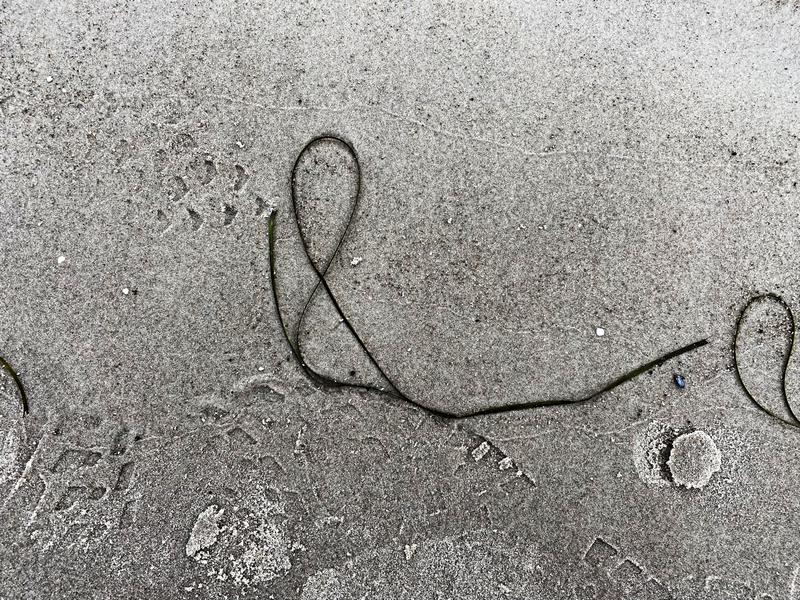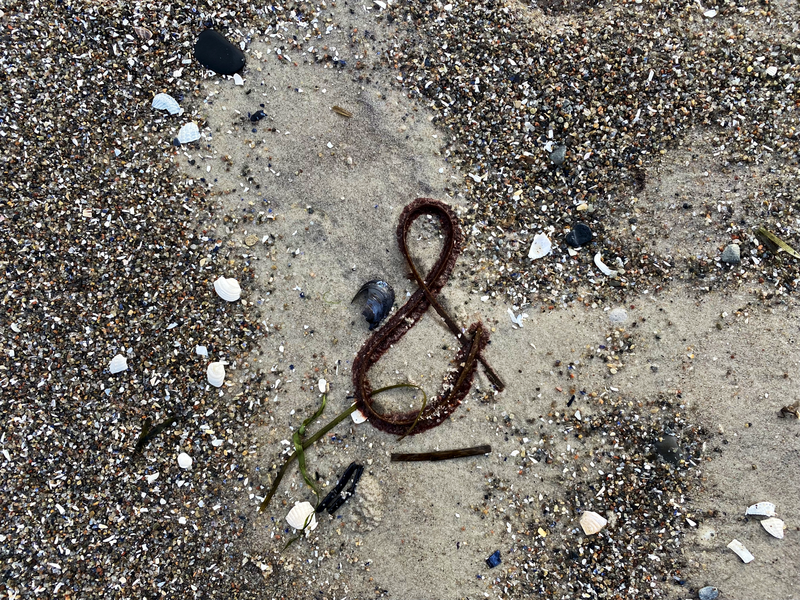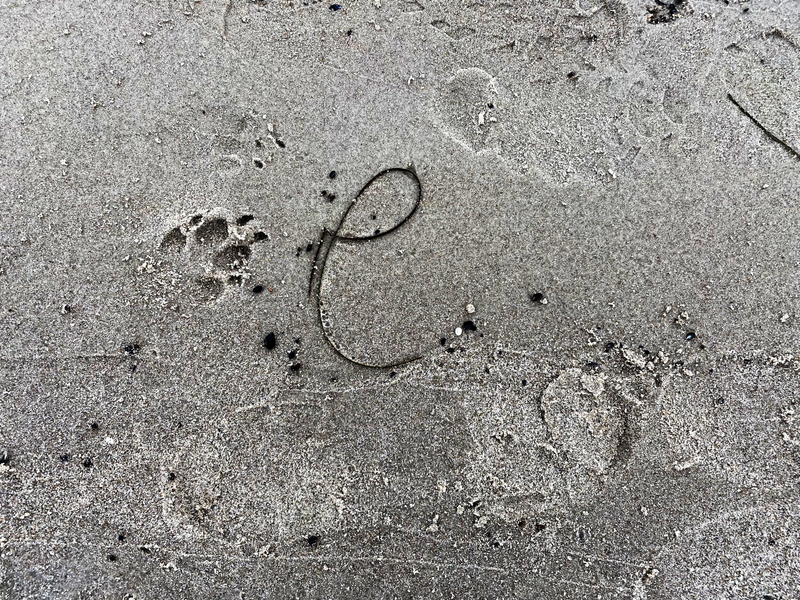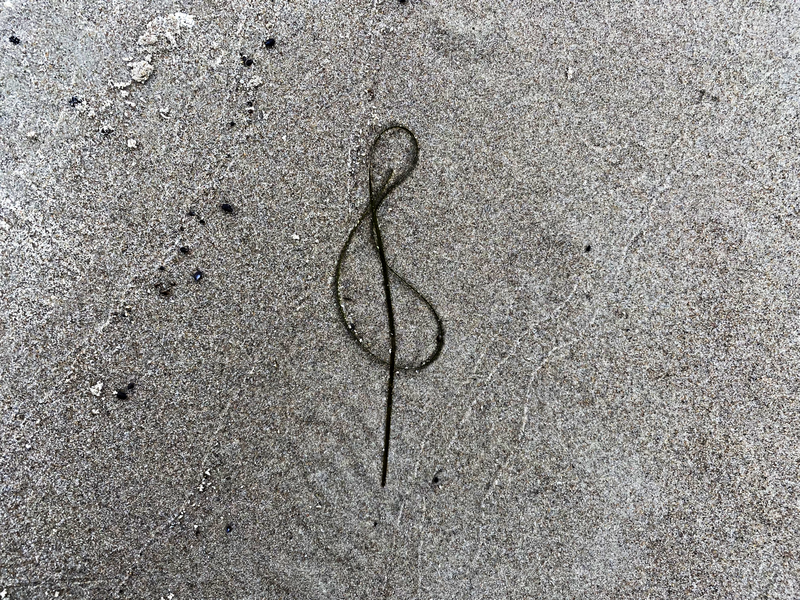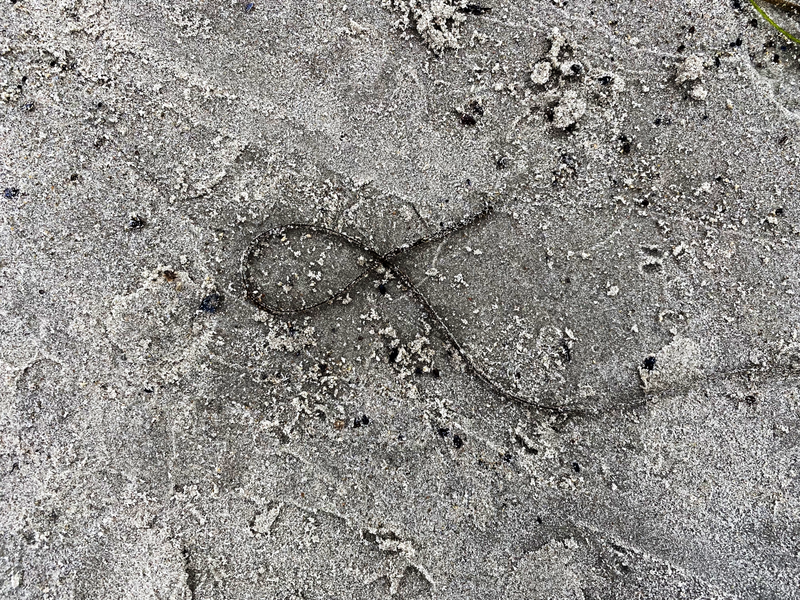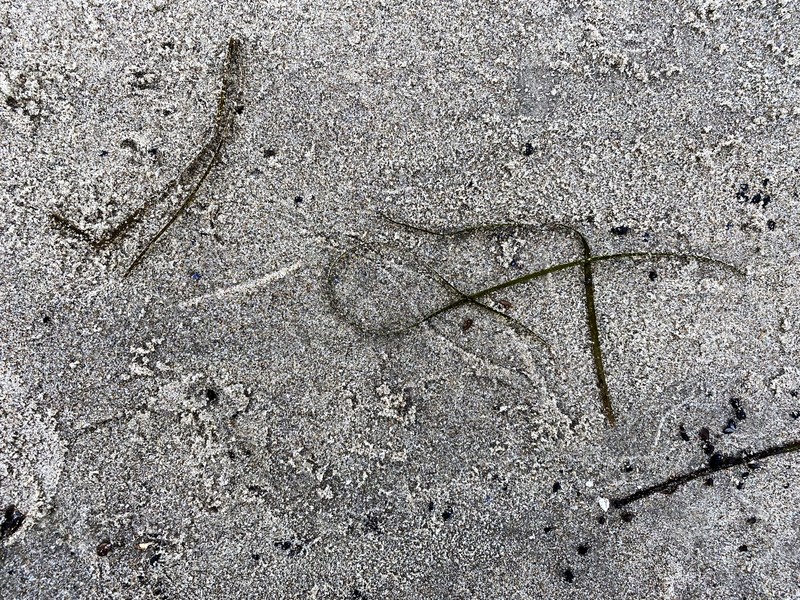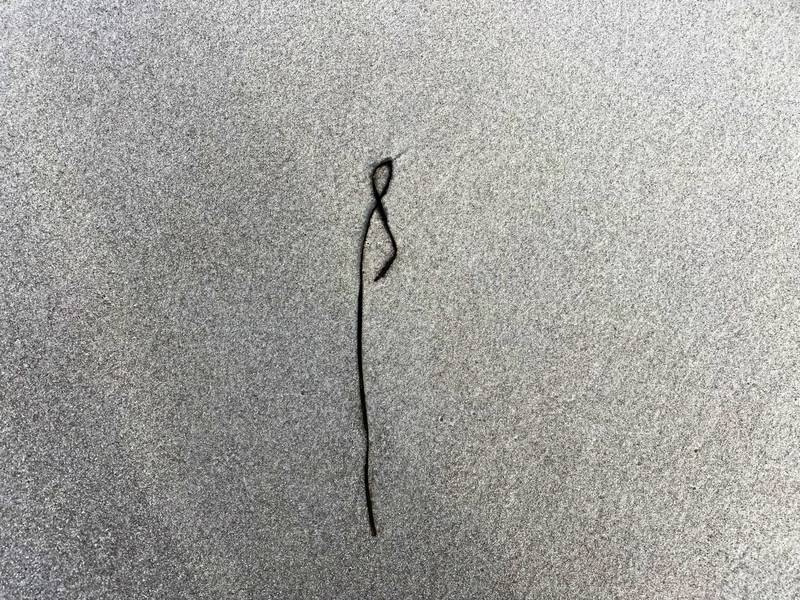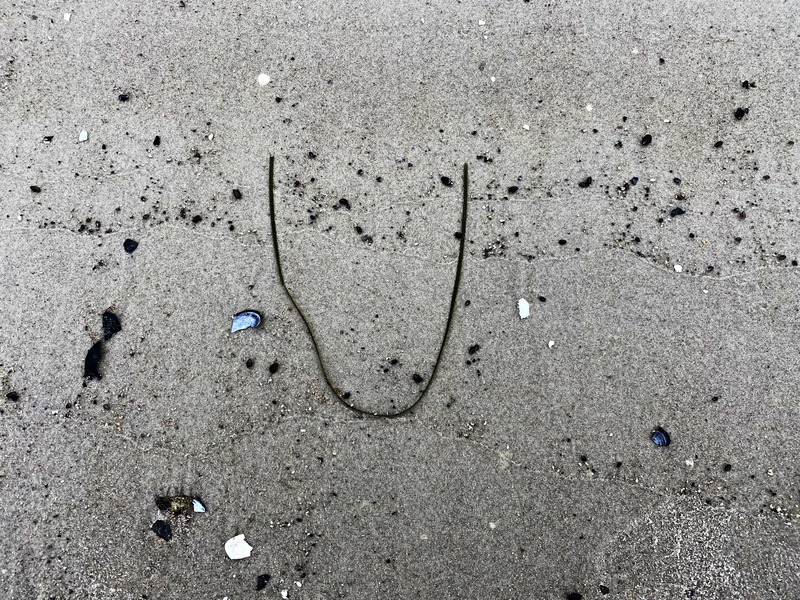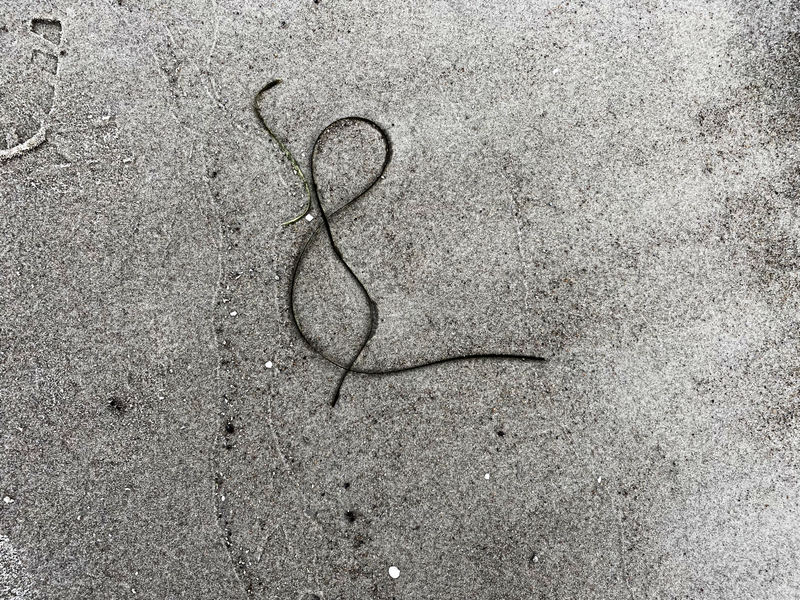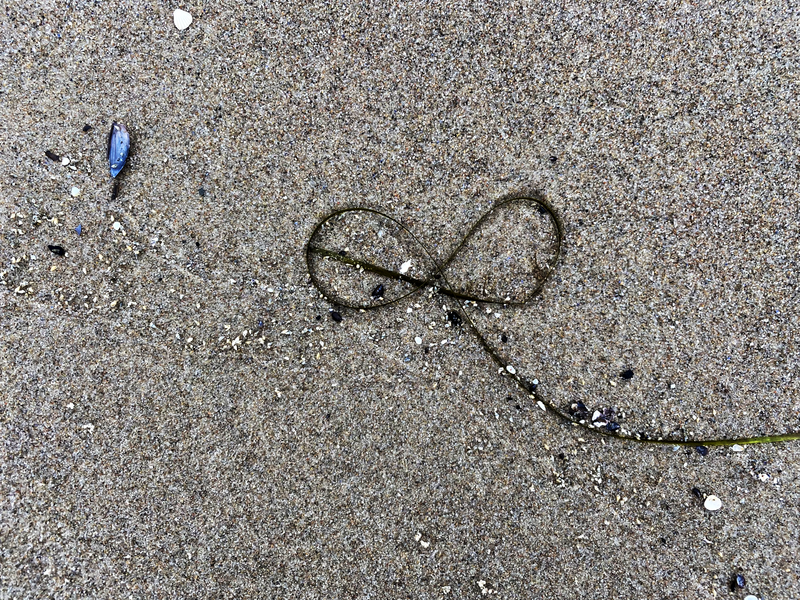
Ostseetypografie Teil 9 - Seegras-Typografie 2022
In den Herbstferien ging es wie jedes Jahr an die Ostsee auf die Insel Rügen.
Bei langen Strandspaziergängen bin ich wieder schwach geworden und habe ein weiteres Kapitel Seegras-Typografie aufgeschlagen.
Alle Fotos von Seegras-Zeichen und Buchstaben sind wieder nicht gestellt und oft nur für Bruchteile von Sekunden als Bild sichtbar, bis eine neue Welle sie zerstört oder verändert.
In der Regel entstehen durch die Wellen meist runde Formen. Am häufigsten kann man des kleine griechische Alpha erkennen. Auch wunderschöne &-Zeichen entstehen durch Wind und Wellen. Cool ist auch das große „J“, welches ich für einen kurzen Moment am Strand entdeckt habe.
Eckige Formen entstehen eher selten. Ich kann zumindest mit einem schönen großen „V” aufwarten.
Hier meine gesammelten Seegras-Zeichen. Viel Spaß beim Entdecken und alle Zeichen sind aus reiner Natur, also ökologisch vollkommen klimaneutral :)).
Alphazeichen - im Entstehen und fertig …
&-Zeichen im Entstehen und fertig …
Schöne J - Zeichen …
Eher selten - eckige Buchstaben aus Seegras …
Jede Menge ander Buchstaben und Zeichen aus Seegras …